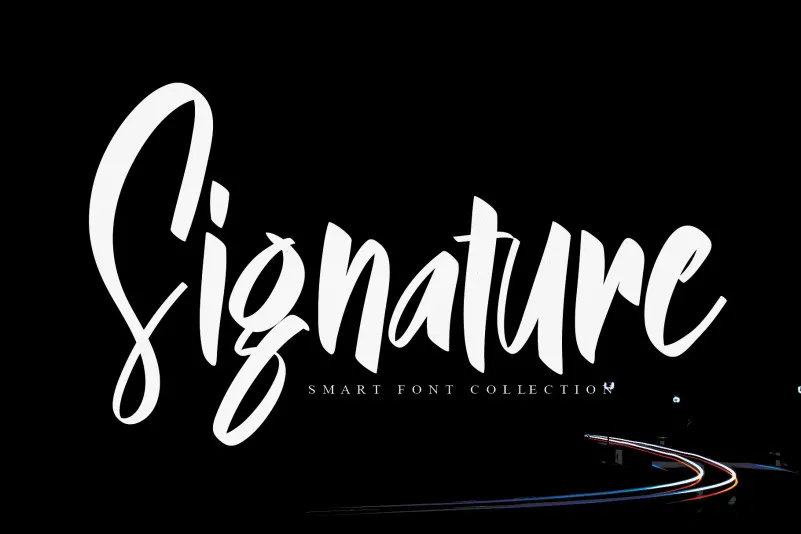
Esta é uma fonte feita com estilo de escrita manuscrita, firme e atraente. Ela se destaca pela sua leitura fácil e por ter linhas arredondadas perfeitas. Este tipo de letra irá transformar seus projetos delicados em verdadeiras obras de arte! Se você está procurando uma fonte que enriqueça seu design, esta é uma excelente escolha para a categoria de script fonts. Signature Font é o ideal para quem busca um estilo elegante e criativo. Suas linhas fluidas e arredondadas são adequadas tanto para aplicações gráficas como escrita digital. Não importa o projeto que você está realizando, essa fonte irá tornar suas criações únicas e imprimíveis.